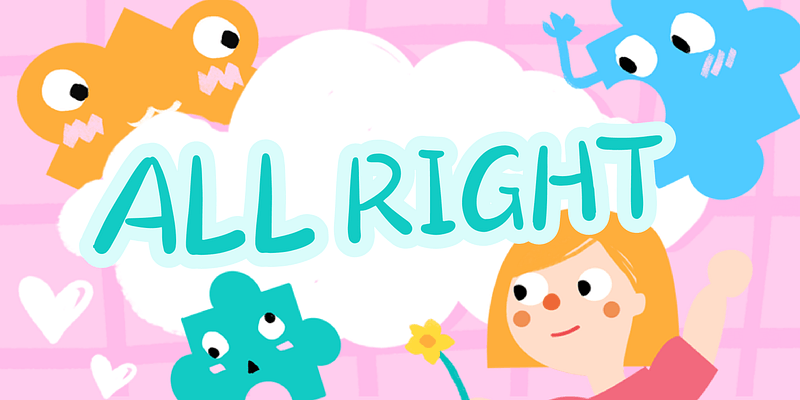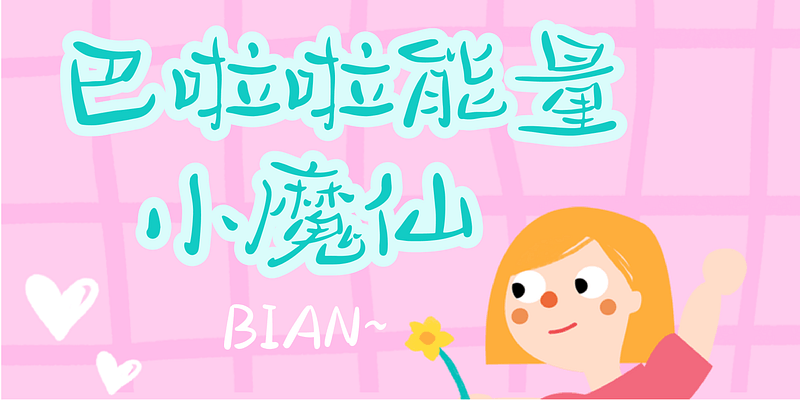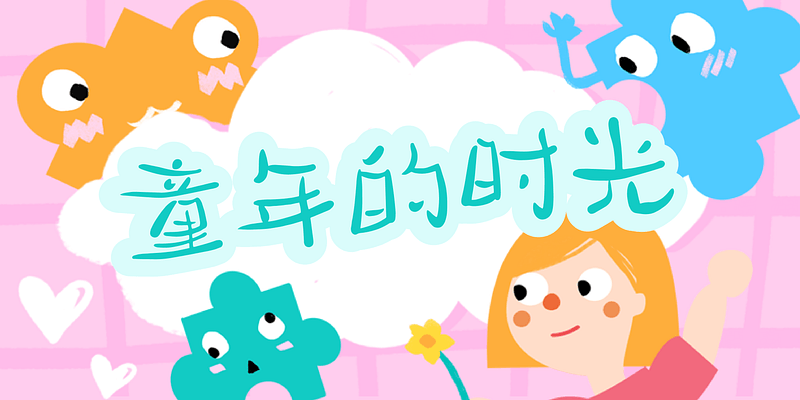
Der Designer verwendet unregelmäßige Striche für strukturelle Zwischenspiele. Die Schrift ändert sich, um die kindliche, ungehemmte Einfachheit widerzuspiegeln, die scheinbar unbeholfen, aber versteckt lebendig ist, so dass jedes Wort einzigartig geworden ist, voller Humor und Spaß.